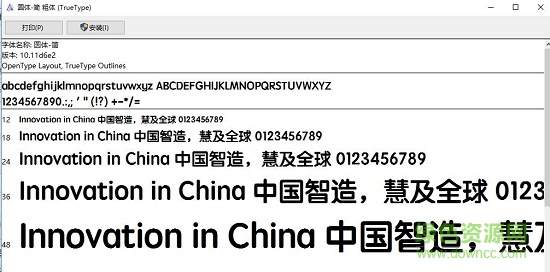
圓體 簡 粗體字體
圓體簡粗體是一款實(shí)用的圓體字體,該字體有極強(qiáng)的筆畫規(guī)律性,字型飽滿,結(jié)構(gòu)平穩(wěn),線條較粗,比較引人注目,喜歡的朋友快來下載吧!
圓體簡粗體特點(diǎn)
字面較大,結(jié)構(gòu)方正,筆形柔和,空隙均勻,適用于正文、廣告、說明等領(lǐng)域。